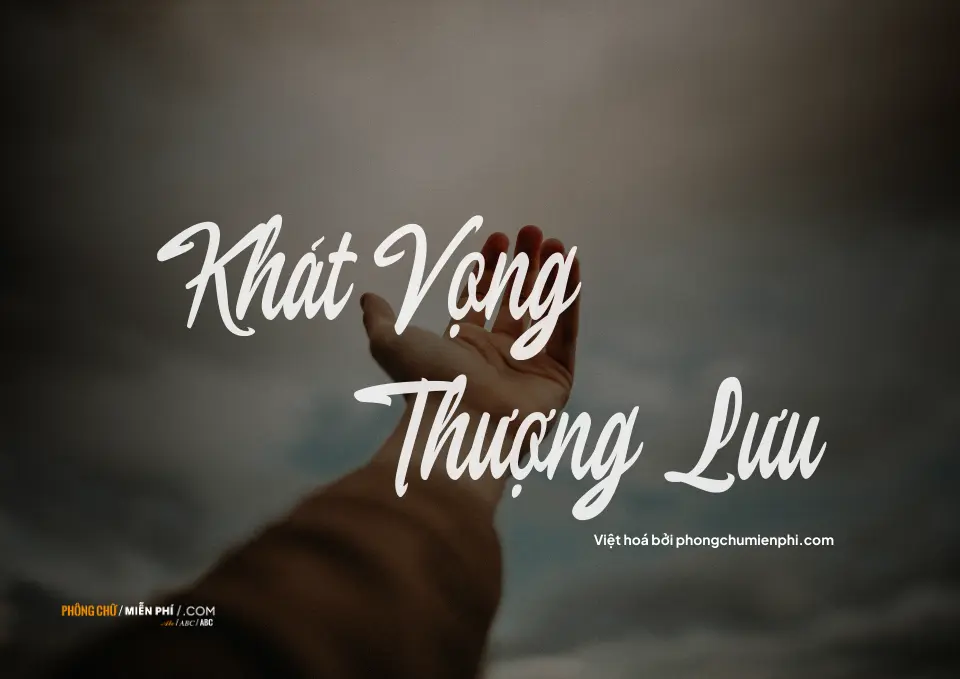
Tên font: Font Việt hoá Pinsmalle Script
PCMP Pinsmalle Script là một phông chữ script kỳ diệu được tạo ra tỉ mỉ với nét thanh lịch. Dù bạn đang tìm kiếm phông chữ cho Instagram hay phông chữ thư pháp cho các dự án DIY, phông chữ này sẽ biến mọi ý tưởng sáng tạo thành một tác phẩm nghệ thuật đích thực!
Đây là một phông chữ viết tay cổ điển đậm nét. Phông chữ này có thể được sử dụng trong nhiều dự án với chủ đề retro/vintage và sang trọng. Các nét cong khiến phông chữ này trông tuyệt vời cho các chữ viết retro mà bạn có thể tạo ra trong nháy mắt! Kiểu phông chữ này được thiết kế hoàn hảo để áp dụng đặc biệt cho logo, tiêu đề, biển báo và các hình thức trang trọng khác như thiệp mời, nhãn, logo, tạp chí, sách, thiệp chúc mừng/thiệp cưới, bao bì, thời trang, mỹ phẩm, văn phòng phẩm, tiểu thuyết, nhãn mác hoặc bất kỳ mục đích quảng cáo nào.